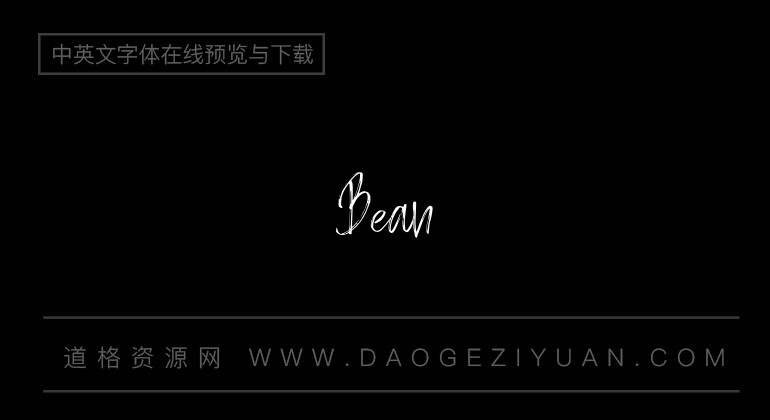
Bean
Bean字体是一种手写风格的字体,其特点是每个字母似乎都是手写的,有一种温馨、亲切和自然的感觉。Bean字体最初是由设计师Amy Dietrich创建的,它在2011年首次发布,现在可以在许多字体库和设计软件中找到。 Bean字体的笔画有点不规则,有些字母看起来有点潦草,但这也是它的独特之处。它适用于许多不同的设计场景,如手写便签、婚礼邀请卡、海报、广告等等。使用Bean字体可以给设计作品带来亲切和个性化的感觉,使其看起来更加自然和人性化。 总的来说,Bean字体是一种非常流行的手写风格字体,使用它可以给设计带来非常独特的效果。
Bean是一款非常不错的手写艺术字体,具有很好的视觉感,适合于文化类的宣传设计、商业类品牌的广告和产品包装设计以及个性化文字排版等较多场景。